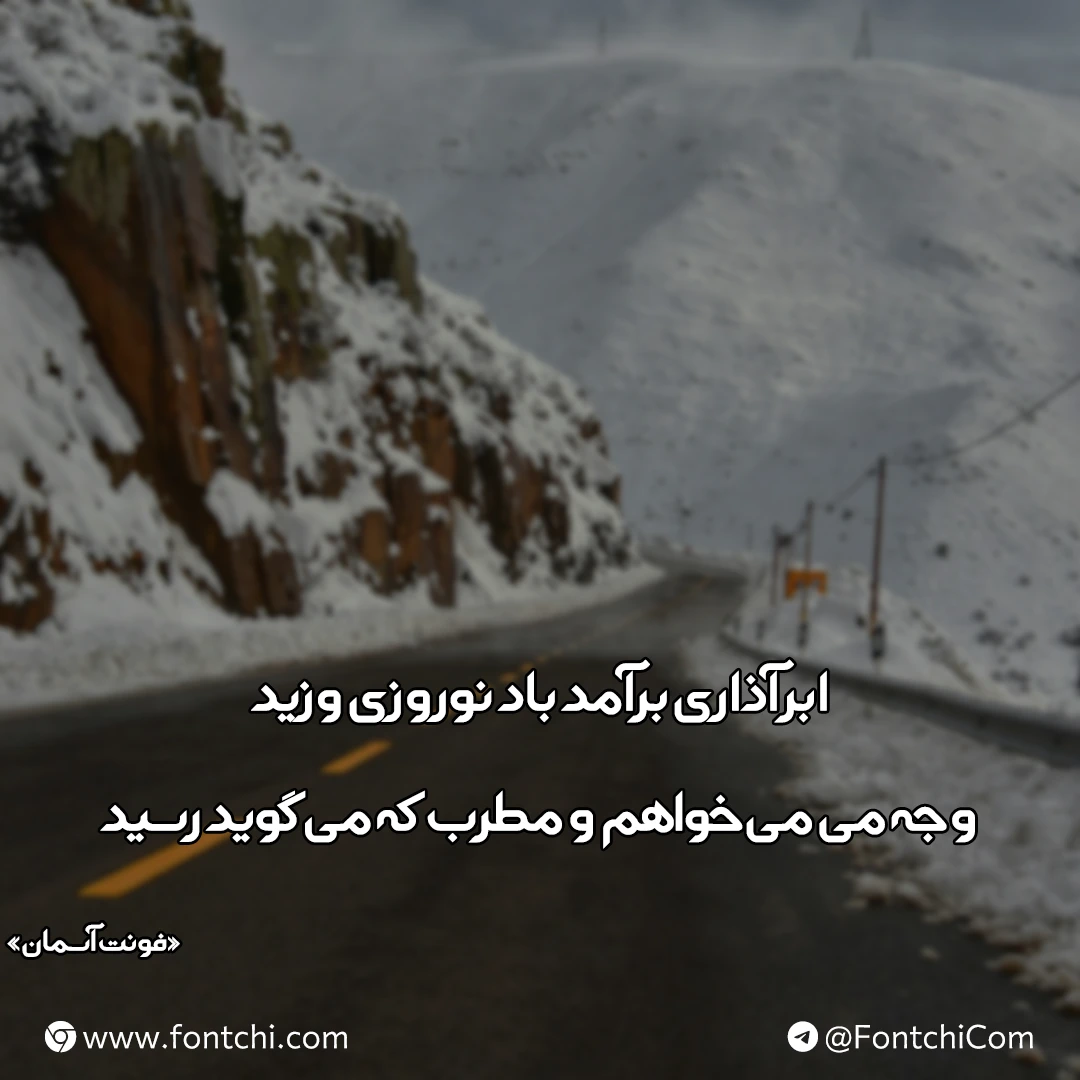
فونت آسمان (G Aseman)
| طراح | قاسم نجاری |
فونت آسمان (به انگلیسی: G Aseman) از سری فونتهای فانتزی برای استفاده در عناوین و متون کوتاه است که با ساختاری هندسی طراحی شده است. در طراحی این فونت از تایپفیس لوگو بانک سامان الهام گرفته شده است که میتوانید از آن برای طراحی لوگوتایپ نیز استفاده کنید.
فونت آسمان TTF از یک وزن معمولی Regular پشتیبانی میکند و فاقد وزنهای دیگر است. سبک طراحی این فونت طوری است که برای استفاده در متون کوتاه و عناوین کاربردی است. استفاده از این فونت در متون بلند توصیه نمیشود. از جمله کاربردهای آن میتوان به موارد زیر اشاره کرد:
- طراحی لوگوتایپ
- استفاده برای عناوین و تیترها
- استفاده به عنوان تامنیل پست و ویدئوهای شبکههای اجتماعی
- استفاده در عنوان جلد کتاب و مجلات خصوصا با طراحی مدرن و بهروز